今回は、久しぶりの提言です。
今回の提言は「落書き本を作ろう」です。
落書き本を作ろう、というのは言いかえると、「本に落書きしよう」ということです。みなさんの身の周りにある本に書込みや落書きをしましょう、ということです。
「本に落書きするなんてけしからん!」という方は、このブログの『なぞってみたシリーズ』のように、本をコピーしてからそのコピーした紙に落書きするのもよいでしょう。
落書きといっても悪ふざけをする必要はありません。「落書き本を作ろう」という言葉にはきつい印象をもたれたかもしれません。まじめに書き込むのもアリです。
真面目な言い方にすると「本に書込みをしよう」というのが、今回の提言です。
1 落書き本のイメージ
さっそく説明に入りましょう。
まずは、落書き本(書き込み本)のイメージを持ってもらいましょう。
京都大学元総長の平澤興先生は、自分が共著者となっている本の大事なところに自ら書き込みをしました。そして、その書き込みによるメッセージがこもった本を、もじのすけ父に贈りました。その本は、もじのすけ父から、もじのすけへと受け継がれています。
以前の記事では、この本をなぞったことがありました。
ご紹介した本の実際の書き込みを実際に見てみましょう。こんな感じです。
例1
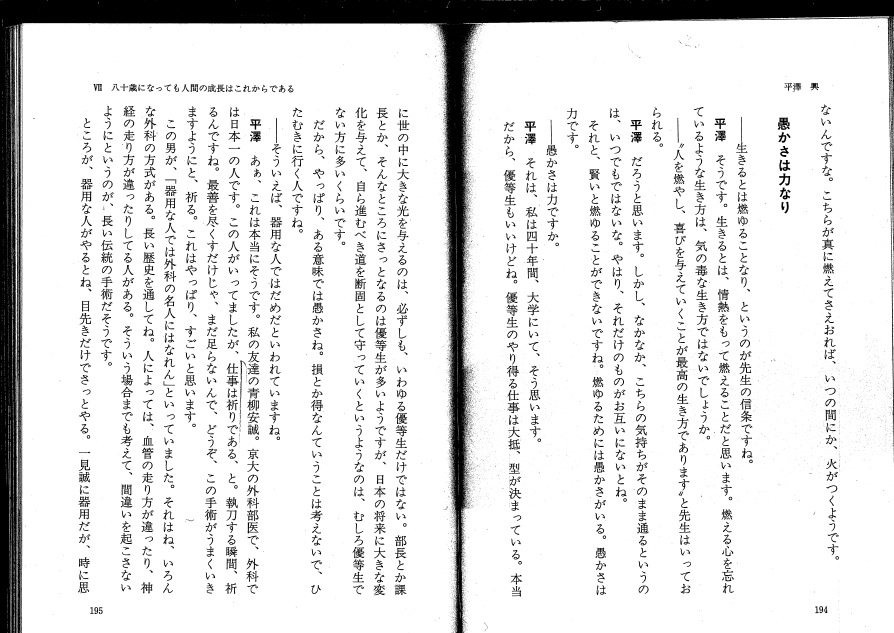
例2
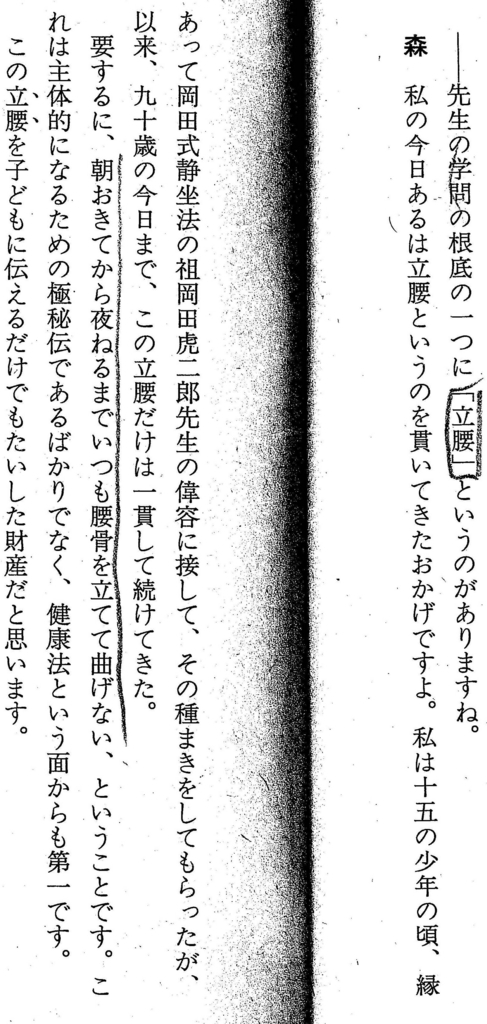
例3
例4
このように書き込みは多くありません。また、線や図形であって、手書き文字の書き込みはありません。
書き込みの入った部分は、他のところにも色々線が引かれています。
なぜ全部を紹介しないか?
それは、単なる出し惜しみです!人間が小っちゃくてすみません!
罪滅ぼしにはなりませんが、もう一度ざっくり見てみましょう。
例1
例2
例3
例4
まっすぐな線がありません。流れるような線やしっかりと書いた線があったり、〇や四角が太かったり、と表情に富んでいます。
みなさんは、書き込みを見られて(読まれて)どう思いましたか。このわずかな書き込みを見るだけでも、書き込んだ人(平澤興)はどこが大事だと思っているのか、がストレートに伝わってきます。
こんな感じで活字の本に書き込みがあると、活字の文章だけのときとは違い、大事なポイントやニュアンスを読むことができます。活字の文章の著者と、書き込みをした人が別の人だと、2人の人から2つの意見を聞かせてもらったような気になります。
これが落書き本(書き込み本)のイメージです。
2 書き込み新聞記事のイメージ
ついでに、本ではないのですが、書き込みの別のケースをご紹介しましょう。それは書き込み新聞記事です。
以前、私は、活字の新聞に書き込みをした記事を書きました。まだ読んでいない人は、活字の文章に書き込みをすることによって、もじのすけの思考が深まっていく様子や活字と手書き文字のアンバランス、コラボレーションを、ぜひその記事で味わってみてください!
新聞は本ではありませんが活字の文章という点では共通です。ある人が新聞を読みながら書き込みし、そして、別の人がその書き込みを読む。
このとき、その別の人は、元々の著者の活字の文章と、そこに書き込んだ人の考え方(いわばセカンドオピニオン)の2つを、同時あるいは時間差で味わえます。
それが
です。記事と画像を挙げておきます。
記事です。
新聞と書込みの画像はこちらです。
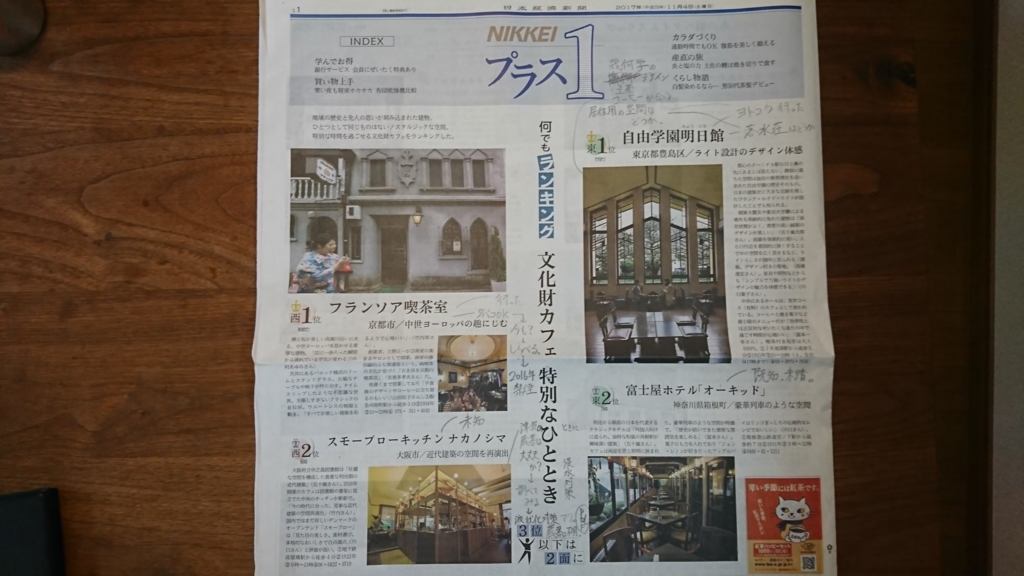
書込みが見えるように拡大します。
例1
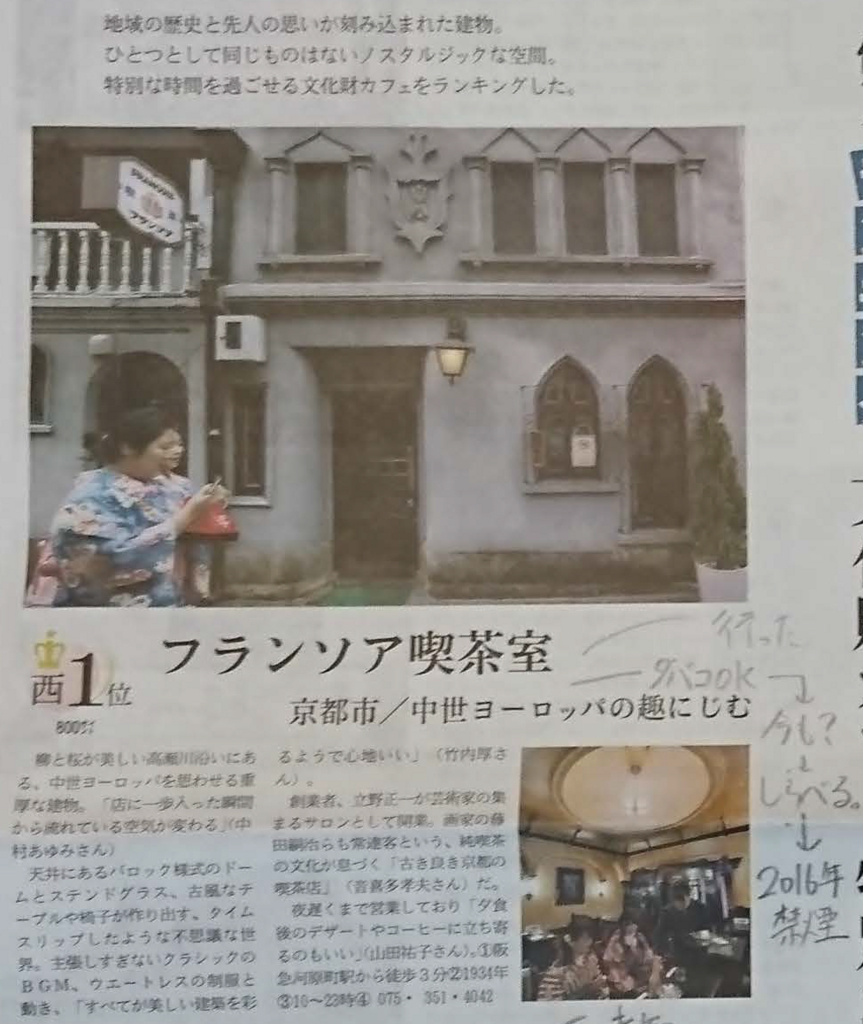
例2
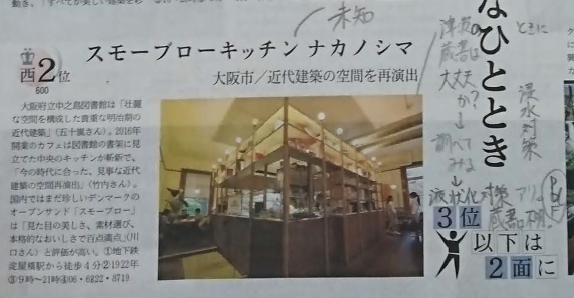
例3
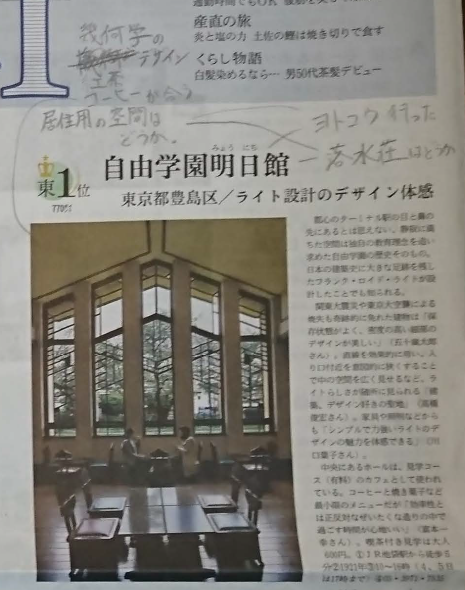
例4
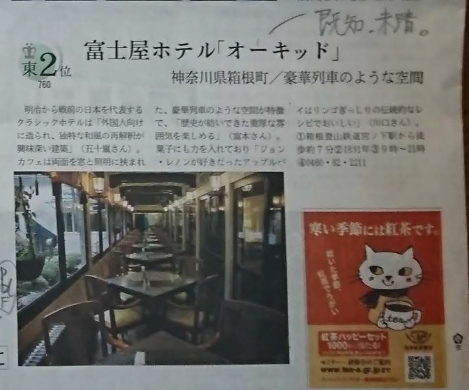
書込みの手書き文字は誤字と訂正線もアリです。文字の大きさも、書く内容も書き込む場所も展開の仕方も 自由です。
こんな感じで、本に書き込みをすると、縦横にキッチリ編集された活字と自由奔放な手書き文字が混在していきます。読んでいるだけだとわかりにくいですが書いているうちにだんだん楽しくなってきます。
小中高のときに教科書に色々落書きをしたワクワク感に近いです。また、友達から落書きした教科書を見せてもらい、面白いものがあれば一緒に笑っていた感覚に近いです。
3 落書き本は書くのも読むのも面白い
本に書き込みをするということは、たとえ絵を描かずに文字や線だけで書き込んだとしても、これは要するに 落書き です。
私は、落書き本を自分で書くのも楽しいですが、こんな感じで自由に楽しそうに、手書き文字や線で落書きしている本を見たいと思っています。
4 落書き本を書く人は誰か
落書き本を書く人に資格は要りません。
誰でも落書きしたくなったら、市販本なら、書いちゃえばいいのです。
ところが、読む立場になってみれば、話がちょっと変わってきます。
もじのすけの場合は、他人の落書き本を読みたいと思うときと、絶対読みたくないときが、はっきりと分かれます。
私が他人の落書き本を読みたくないときはどんなときか。
それは、活字の文章をストレートに読みたいときです。
また、書き込みをした他人が誰か、全く知らないときです。
逆に、他人の落書き本を読みたいときはどんなときか。
それは、落書きした他人が有名人であったり、個性がある人だったときです。
想像してみてください。
あまり面白くなさそうな本があったとします。あまり読む気は起きませんよね。
でも、みなさんが好きな芸能人やスポーツ選手を思い浮かべてみてください。
その芸能人やスポーツ選手が書き込みをしていたら、急にその本が気になってきませんか。「あの人(有名人)は、どんなことを考えているのだろう。落書きを見ると結構わかってきそう。」と思えてきませんか。
私だったら、誰の落書き本が見たいか。
有名な経営者、俳優、歌手、スポーツ選手、作家、音楽家、ビジネスマン、職人、学者、政治家・・・。ミーハーなので、とにかく有名人なら誰でもいいです!
有名人でない場合には、どんな人の落書き本が読みたいか。
それは、異常に成績がいい東大生とか、めちゃくちゃ賢い人とか(アバウトですみません)。・・・ミーハーなので、やっぱりどれも気になります!
新作の本が発売されると、その帯に有名人が推薦文を書いたりしますよね。
私は、その帯の推薦文を読まされるくらいなら、有名人である推薦者には、その本に落書きをしてもらい、その落書きごと本を買って読みたい。
そして、有名人がどこに食いついたのか、を味わいながら、その落書きも込みでその新作本を読みたいです。その方がお世辞が入った推薦文よりもリアルで面白いと思うのです。
結局、本に落書きをすべきなのは誰でしょうか。
書く方の立場になれば、誰でもよい。
もじのすけでもよいし、このブログを読まれた皆さんの誰でもよい。
面白そうだと思った人は、ぜひ本に落書きしましょう!
もう一度自分に問いかけてみます。
本に落書きをすべきなのは誰でしょうか。
読む方の立場になれば、有名人や個性的な人です。
有名な経営者、俳優、歌手、スポーツ選手、作家、音楽家、ビジネスマン、職人、学者、政治家、歴史上の人物・・・。有名人でなくても、異常に成績がいい東大生とか、めちゃくちゃ賢い人とか。
ですが、このような内容の濃い本でなくてもいいです。
落書き本を作ることは、手書き文字の復権という意味がありますし、有名人の落書き本であれば、ビジネス上も意味があります。それらのことをもう少し具体的にお話ししようと思います。次回に。